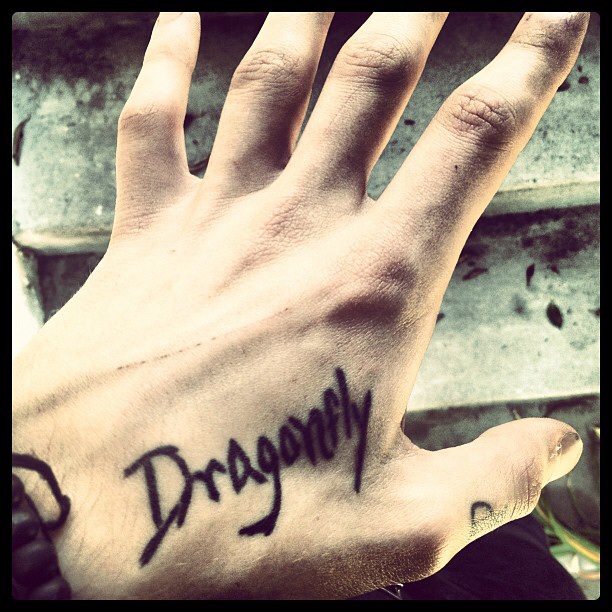
Suche diese Tattooschrift!
Kann mir jemand sagen, welche Schriftart dieses Tattoo hat? Oder vllt. eine ähnliche mir nennen? Danke^^
PS: Das Tattoo ist von Andy Biersack
Das ist sicherlich handgezeichnet, so zusammengewürfelt wie die Buchstaben aussehen. Und wenn du nicht allzu viel Text in so einer Schrift haben willst, kann man die fehlenden Zeichen auch relativ schnell ergänzen.
Ansonsten haben wir hier eine Liste von Tattoo-Schriften, da du aber wahrscheinlich für die Schrift kein Geld ausgeben willst, guck doch mal bei dafont.com und suche nach Tattoo.
Toll ist das alles nicht und imho sollte eine tätowierte Schrift schon individueller sein, als irgendein Font überhaupt sein kann ...
Naja also der Text, den ich in dieser "Schriftart" haben möchte, lautet folgendermaßen:
Stand up for what you believe in, even if it means standing alone.
Ich hab leider gar keine Ahnung, wie ich die fehlenden Zeichen ergänzen soll. Hab es zwar probiert, sah aber blöd aus...
Ich hab schon mal nach Tattoo-Schriften geschaut, aber keine gefällt mir...
Willst Du Dir wirklich so einen Kalenderspruch in so einer Schrift, die nach unausgegorenem Freefont aussieht inklusive Grammatikfehler stechen lassen? Das Zeug geht später ziemlich schlecht wieder ab. :tutor:
Gerade für so einen langen Text würde ich nicht so eine ›kaputte‹ Schrift nehmen. Das klappt mit einer schönen Script mit optimierten Verbünden und Anschlüssen wesentlich besser (wenn’s nicht nach Knasttattoo aussehen soll).
Also erstens hab ich nicht nach einer Meinung zu dem Spruch gefragt, zweitens ist mir sehr wohl bewusst, dass man ein Tattoo für immer hat (außer man lässt es teuer weglasern) und drittens mag ich die Schriftart. Es ist mein Körper und ich wollte nur Hilfe zu der Schrift haben, keine Kommentare. Und welchen Grammatikfehler bitte? Trotzdem danke!
… und drittens erweist es sich in Foren oft als hilfreich, »über den Tellerrand hinaus« zu antworten, weil so dem Fragesteller unter Umständen neue Perspektiven eröffnet werden. Aber auch wenn das in Deinem Fall nicht so sein sollte, empfinde ich es, viertens, als ungehörig, in einem Forum, das von der Freiwilligkeit der Antwortenden lebt, so pampig zu reagieren.
Apropos Tellerrand,
Sarah, was man versucht hat, dir in lieben und netten Worten beizubringen: wenn du einen Ritualmörderfont als Tattoo-Vorlage nimmst, hast du Wiederholungen drin, die gleichermaßen auffällig wie hässlich sind.
Bevor man dann alles individualisiert, kann man besser gleich den Stecher deines Vertrauens um eine originäre Schriftprobe bitten.
Müßte es nicht »… means to stand alone« statt »… means standing alone« heißen?
empfinde ich es, viertens, als ungehörig, in einem Forum, das von der Freiwilligkeit der Antwortenden lebt, so pampig zu reagieren.
Les  jetzt in Sarahs Antwort weniger Pampigkeit denn Klarstellung. Finde den Ehrgeiz, erzieherisch wirken zu wollen, hier mitunter etwas übertrieben.
Ich finde aber auch, dass jeder für sich selber entscheiden darf, was er schön findet. Ich wollte halt nur was zur Schrift wissen, die im übrigen keine Ritualmörderschrift ist, auch wenn einige das so sehen. Man kann übrigens 'means standing alone' und 'means to stand alone' schreiben, ist beides richtig. Trotzdem DANKE für die vielen Tipps, Anregungen, liebevoll gemeinten Hinweise. Falls mir jemand mit 'meiner' Schrift noch weiterhelfen kann oder möchte, dann nehme ich die Hilfe sehr gerne an.
Finde den Ehrgeiz, erzieherisch wirken zu wollen, hier mitunter etwas übertrieben.
Wenn auch nur die geringste Chance besteht, einen jungen Menschen von einer Dummheit abzuhalten, kann man es ja zumindest mal versuchen.
Ich finde aber auch, dass jeder für sich selber entscheiden darf, was er schön findet.
… und jeder darf das kommentieren, wohlwollend oder ablehnend. Das ist die andere Seite der Freiheit.
Ich glaube, dass das hier keinen Sinn mehr hat, da keiner vor hat mir zu helfen... Wünsche allen noch einen schönen Abend!
Wie gesagt würde ich bei dem Beispiel nicht von einer Schriftart sprechen, da die Buchstaben doch recht unterschiedlich sind. Deswegen würde ich sowas auch nicht für längere Texte benutzen. Nur weil es bei einem Wort gefällt, muss es nicht bei einem ganzen Satz gut aussehen (gerade wenn diese abweichenden Formen öfter vorkommen wirkt es sehr wenig authentisch)...
Das ist als würde man bei jeder Webfont-Anfrage fragen, ob man das mit diesem Internet wirklich machen muss, persönlich kommunizieren ist doch viel normaler und natürlicher ...
Les  jetzt in Sarahs Antwort weniger Pampigkeit denn Klarstellung.
Ich würde dann aber sagen, dass die kritisierten Beiträge auch nur klarstellen, welche Reaktionen Menschen erwarten sollten, wenn sie solche Binsenweish… Aussagen zur Schau stellen. Von daher: nix als klarstellende Hilfsbereitschaft von allen Seiten.